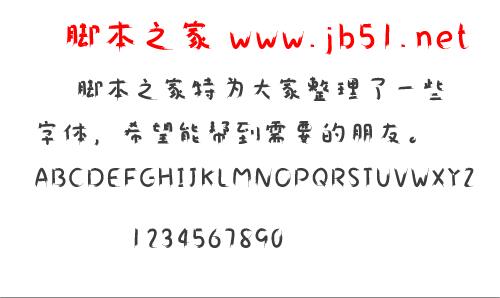
仓耳涂鸦体W03是一款十分好用,且非常漂亮的中文字体,该字体书写简洁工整,用笔流畅自然,形态端正,整体看上去非常好看,适合应用于艺术设计、平面宣传设计、网页设计,书法字帖等领域,也可以应用于文本装潢、信息展示、篆刻制模英文、数据制作、装潢设计、视觉设计、字帖等一切合法应用场景,有喜欢的朋友可免费下载收藏。